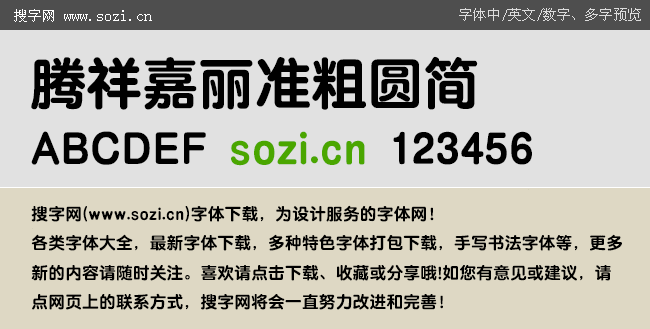
騰祥嘉麗準(zhǔn)粗圓簡(jiǎn)
搜字網(wǎng)提供一款騰祥嘉麗準(zhǔn)粗圓簡(jiǎn)中文藝術(shù)字體下載,騰祥嘉麗準(zhǔn)粗圓是一款應(yīng)用于設(shè)計(jì)方面的簡(jiǎn)體中文漢字,該字體線條簡(jiǎn)潔圓潤(rùn),字形大方得體,整體效果出眾,并且字庫(kù)完整,可用于藝術(shù)設(shè)計(jì)、包裝印刷、簽名設(shè)計(jì)、圖形設(shè)計(jì)等領(lǐng)域。